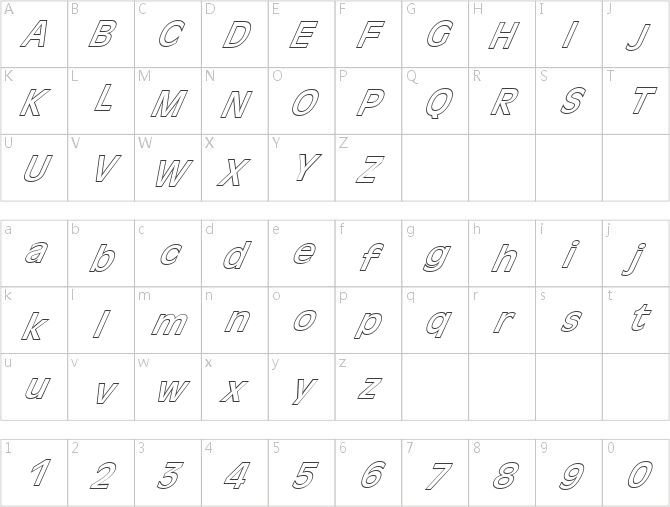
FZ BASIC 2 HOLLOW ITALIC 詳情頁
FZ BASIC 2 HOLLOW ITALIC字體字庫是一款讓人賞心悅目、百看不厭的英文字體,適合各類廣告和產(chǎn)品包裝設(shè)計應(yīng)用,字體大小0.07MB,格式為ttf字體,上傳用戶是惠祥博達(dá),作者/版權(quán)方為未知